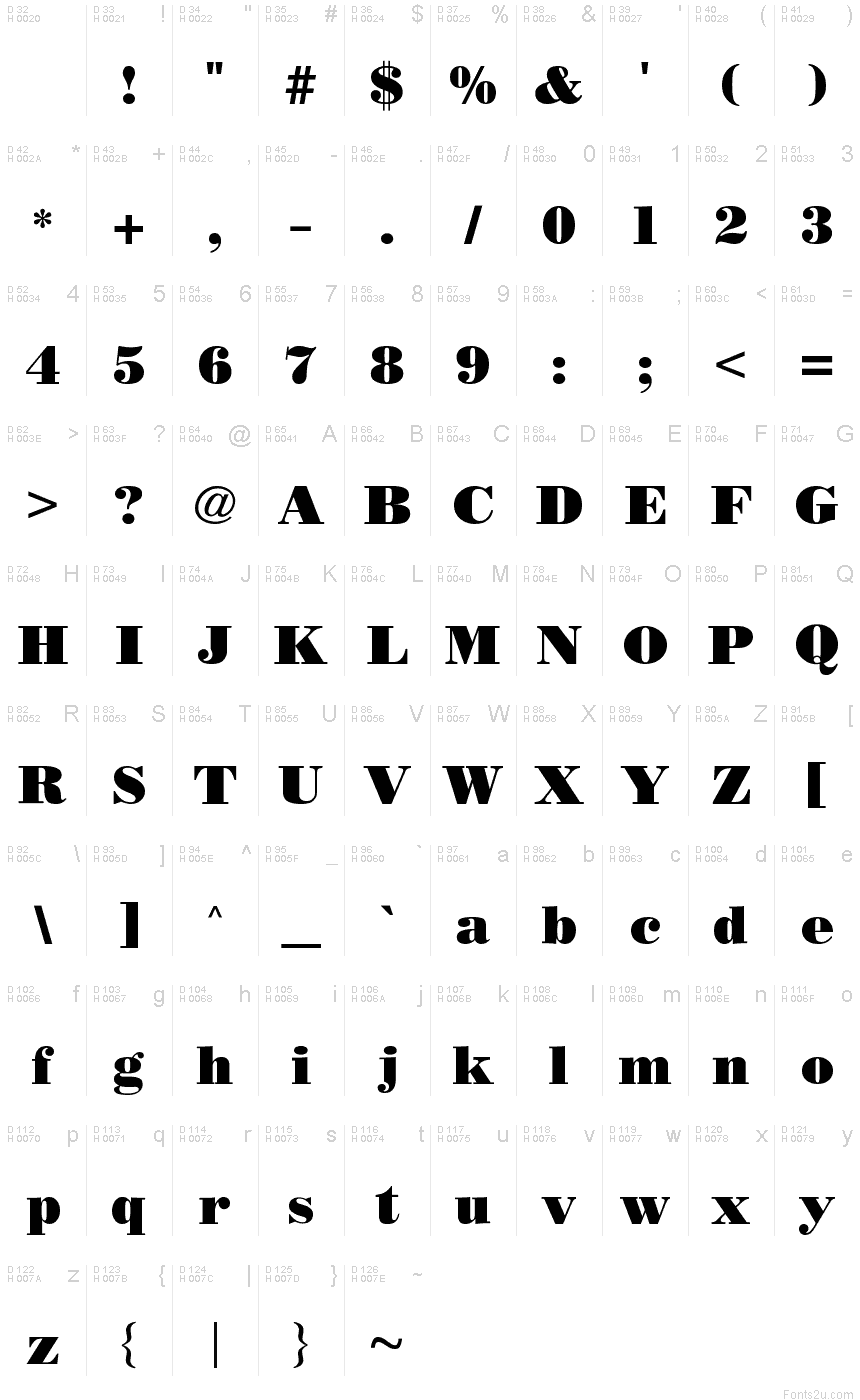
Bodidly bold to darmowy krój szeryfowy, który uderza w stronę niczym pieczątka. Masywne pionowe słupki i ciasno upakowane litery tworzą gęstą, mocną teksturę, podczas gdy wąskie prześwity wewnątrz wycinają ostre fragmenty bieli. Krój wydaje się jednocześnie vintage i brutalistyczny, zamieniając każde słowo w graficzny blok, który niemal można wziąć do ręki.
Dzięki Bodidly bold krótkie nagłówki i znaki graficzne natychmiast zyskują ostrość, co czyni ją naturalnym wyborem do plakatów, okładek, logo, opakowań, obwolut książek i wyrazistych nagłówków na stronach www. Ten darmowy font świetnie sprawdza się w większych rozmiarach, gdzie jego ciężki rytm może w pełni wybrzmieć. Dla zachowania równowagi zestaw Bodidly bold z prostym, dyskretnym bezszeryfowym krojem w tekście głównym, pozwalając, by to jego silna szeryfowa osobowość grała główną rolę.